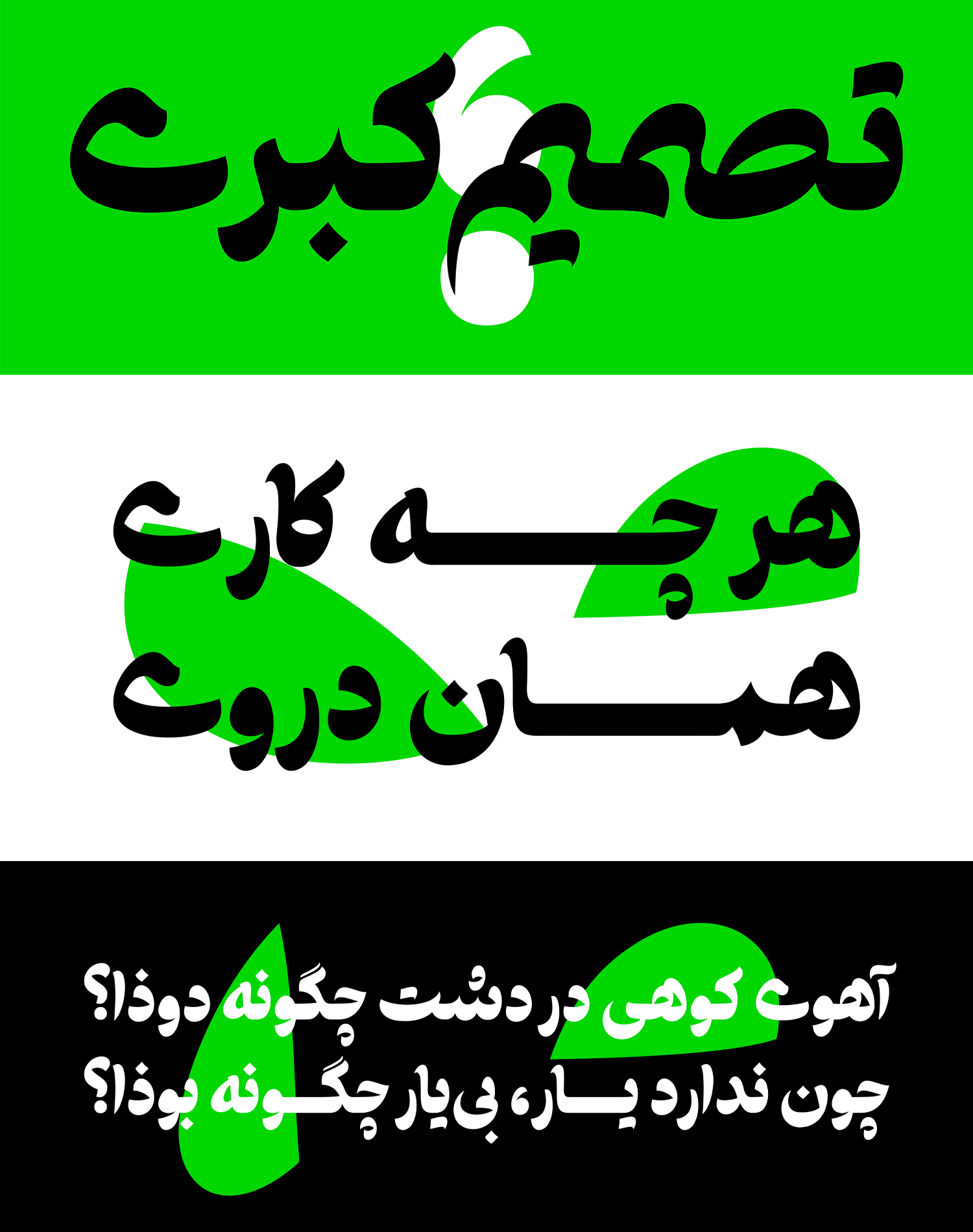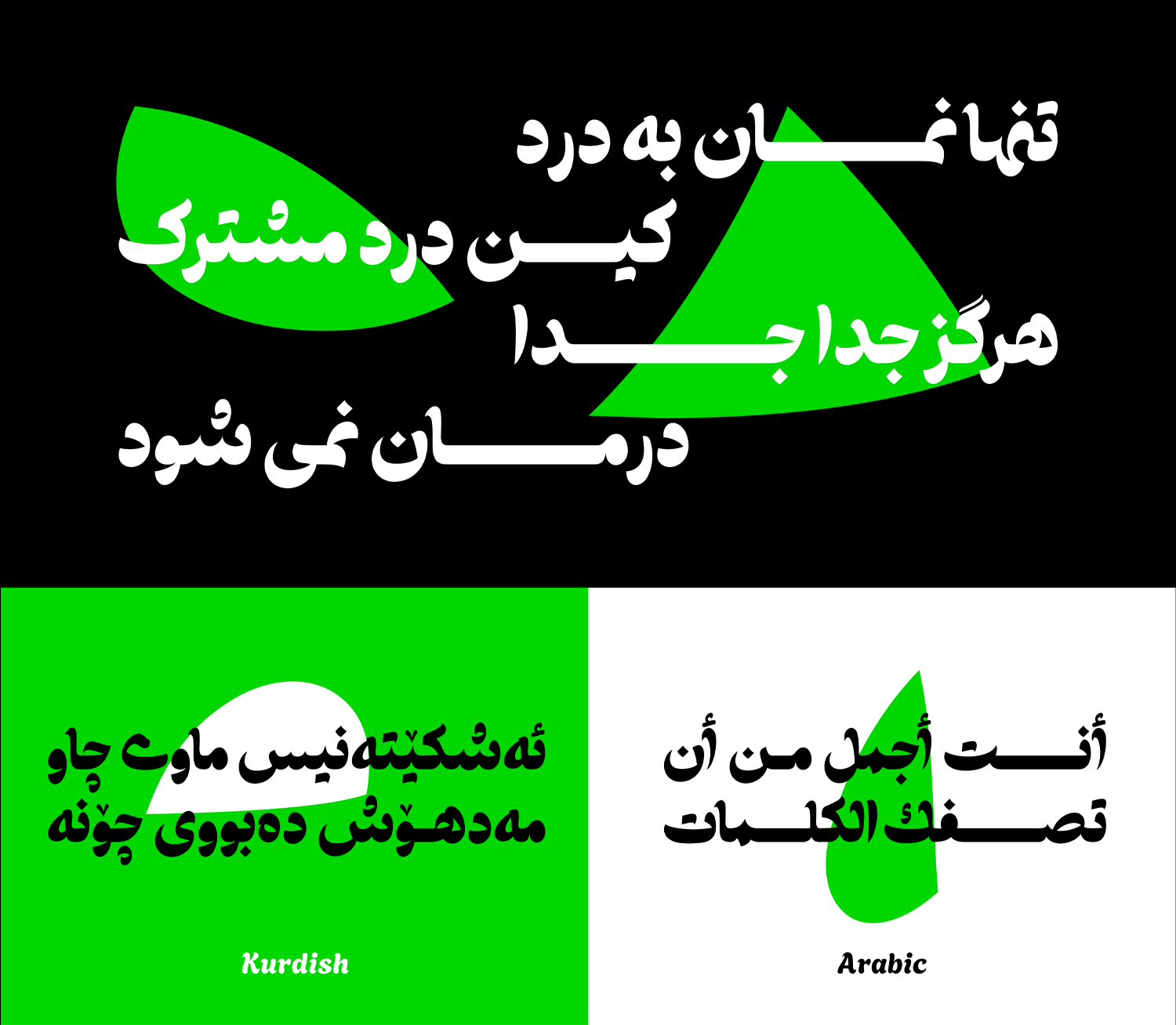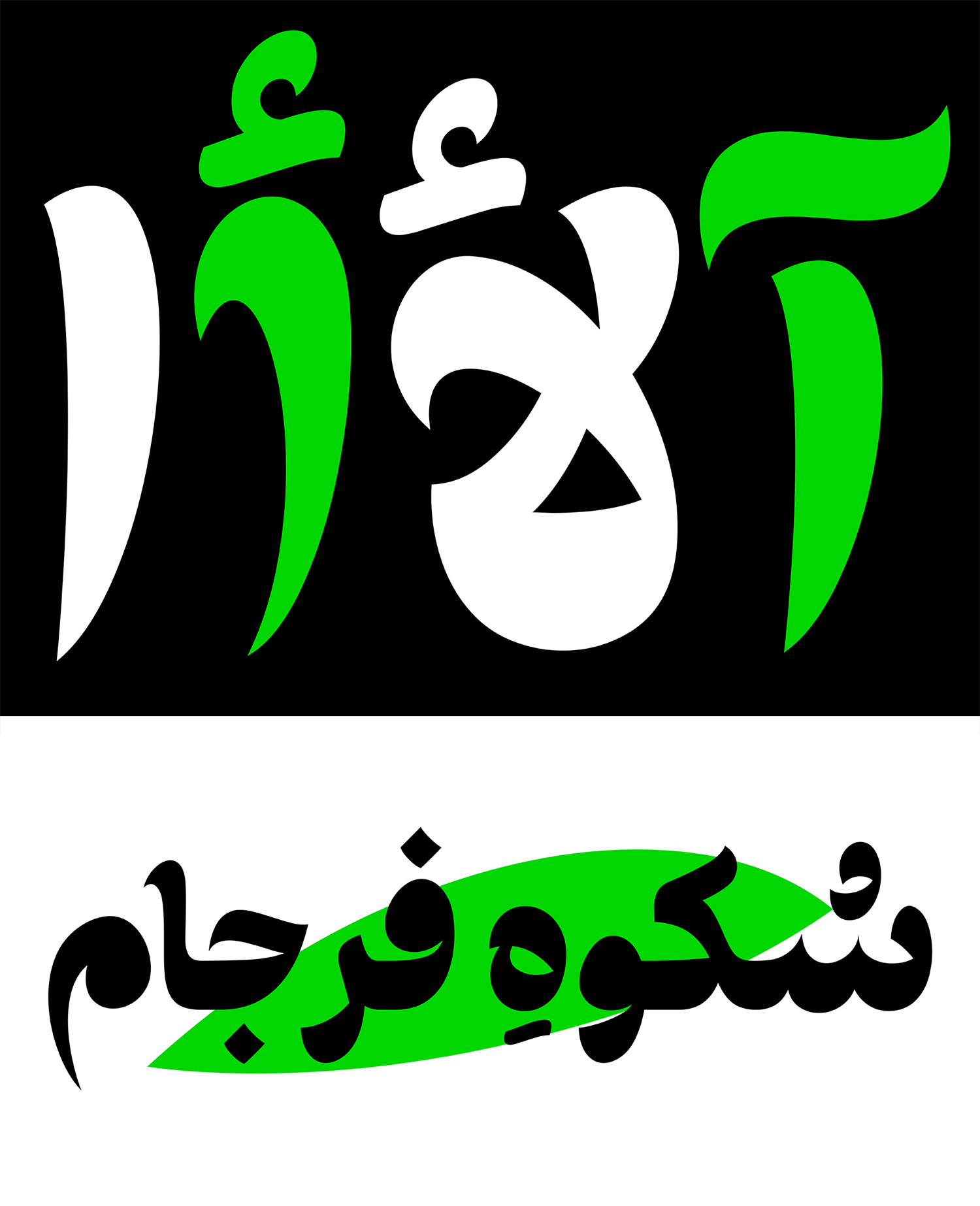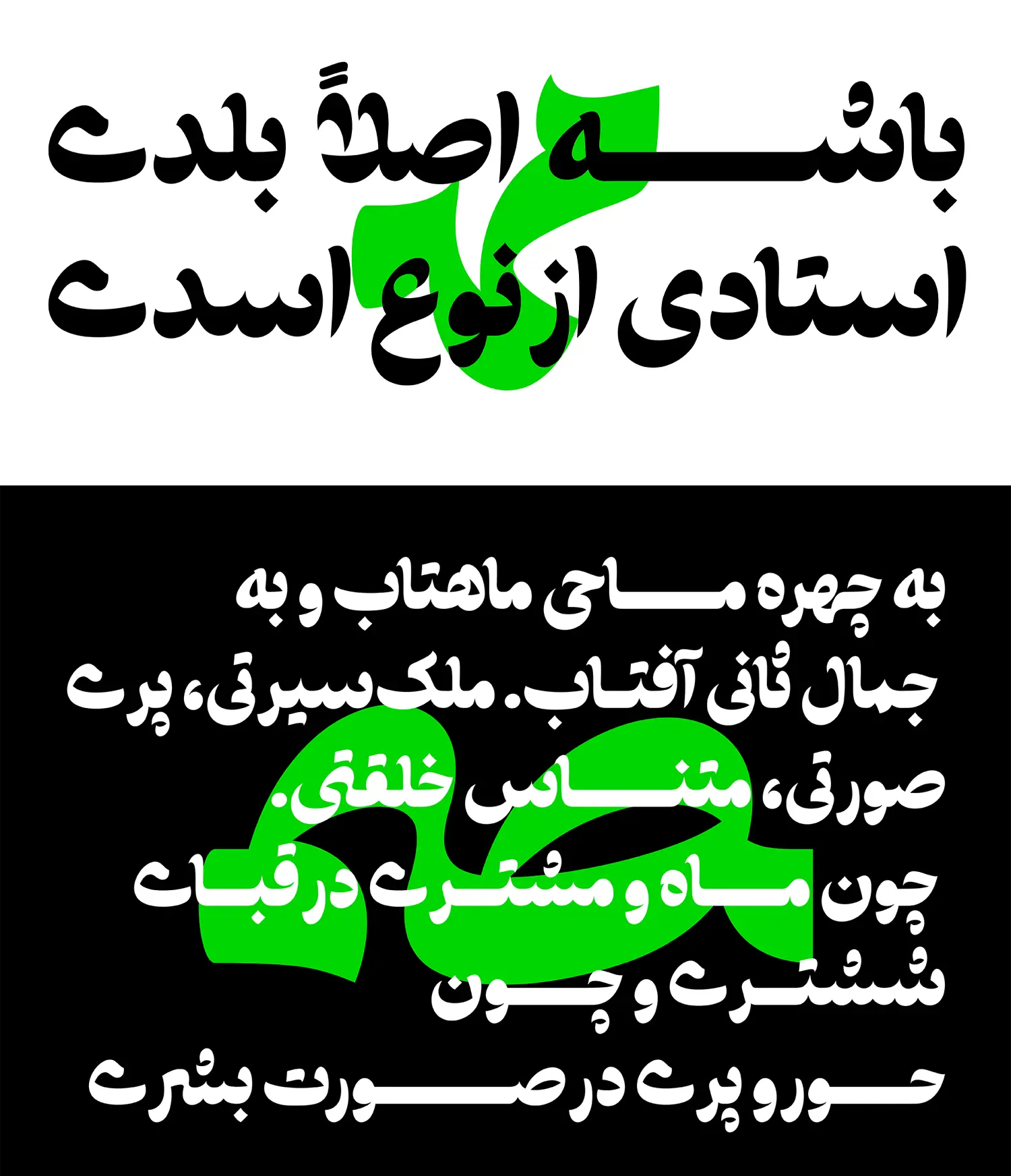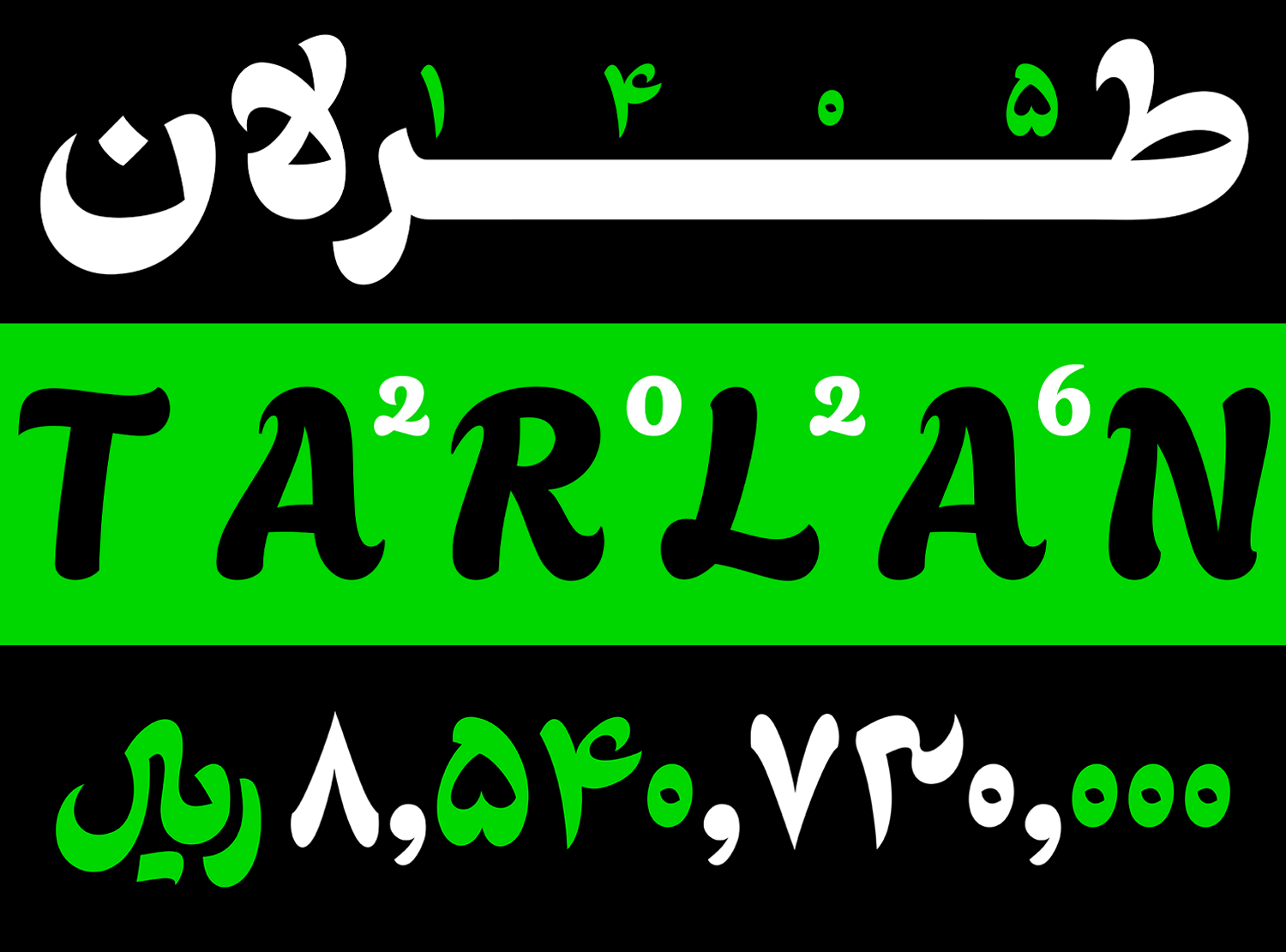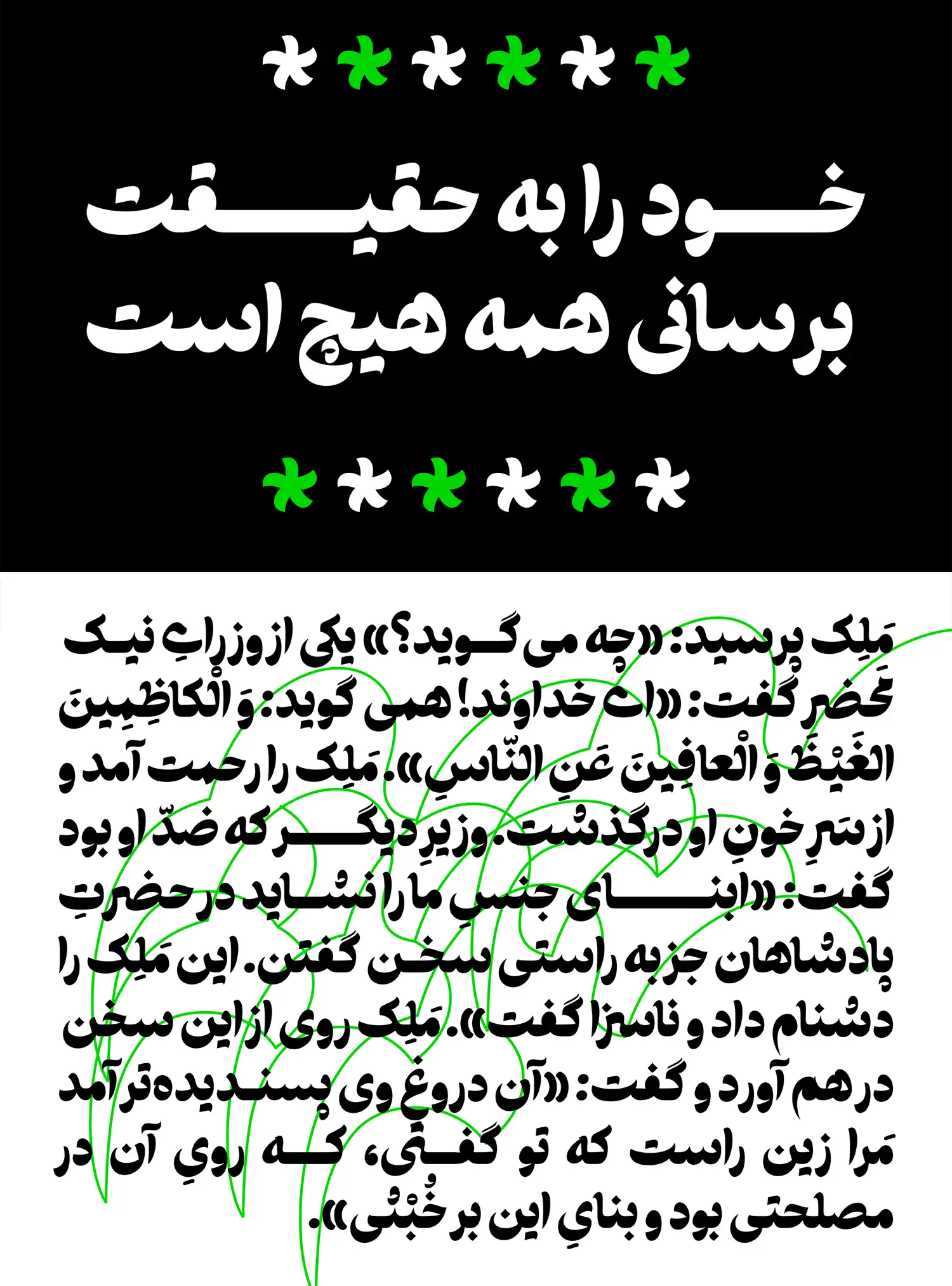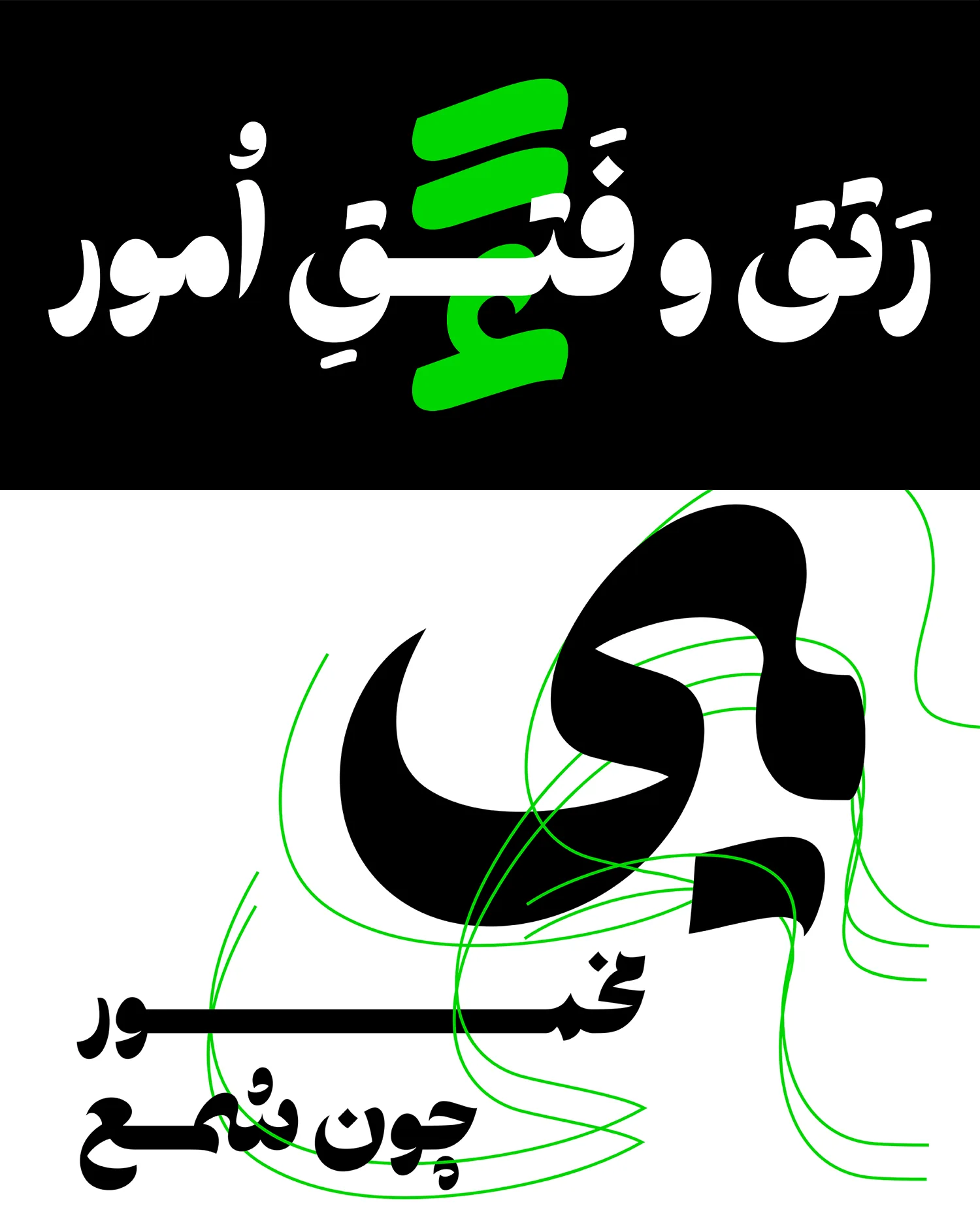
فونت طرلان (Tarlan)
فونت طرلان (به انگلیسی: Tarlan) از سری فونتهای جدید و مدرن امروزی است که بهجای تقلید از خطوط نسخ قدیمی یا مدرنسازی تکراری چنین خطوطی، هویت مختص خود را فریاد میزند. این فونت با باطنی دستنویس، گذشته خود را بهگونهای مدرن و نرم یادآور میشود.
از فونت طرلان میتوانید برای موضوعاتی که جنبه صمیمیت و ایجاد ارتباط با مخاطب دارند استفاده کنید. تبلیغات محیطی و فضای دیجیتال، خصوصا در عناوین یا طراحی پوسترها، این فونت را به اصری خارقالعاده تبدیل کرده است.
نقد و بررسی فونت طرلان (Tarlan)
فونت فارسی طرلان حاصل قلمزدنهای متعدد با مرکب و تجربه مستقیم بر روی کاغذ است. وحید یعقوبلو با ایدهپردازی و طراحی اولیه و امین عابدی با توسعه و فنیسازی آن، اثری خلق کردهاند که بیآنکه خود را مجذوب و محصور در قواعد یک خط سنتی خاص کند، عصاره و حافظه بصری خطوط سنتی مختلف را در قالبی پویا ارائه میدهد.
نام «طرلان» به معنای شاهین و پرندهای تیزبین، دقیقا پس از کامل شدن ساختار حروف انتخاب شد؛ نامی که اصالت، پویایی و انتهای تیز و پرانرژی قلم را به زیبایی روایت میکند.
بررسی هویت بصری و ویژگیهای ساختاری
اگر به تصاویر پیشنمایش این فونت دقت کنید، بررسی این نمونهها و فرم حروف طرلان، چند نقطه عطف مهم را آشکار میسازد:
- تناسبات فشرده و قوسهای پیوسته: حروف در طرلان ساختاری منسجم و فشرده دارند که باعث میشود کلمات کنار هم، ریتمی منظم و در عین حال روان ایجاد کنند.
- انتهای تیز قلم و حس دستنویس: برشهای انتهای حروف و حرکات قلم، حس زنده بودن خط دستی و سنت خوشنویسی با قلمنی و مرکب را منتقل میکنند.
- حضور قوی در عین حفظ خوانایی: طرلان یک تایپفیس تکوزن (Single Weight) است که تمرکز خود را روی جلب توجه در عناوین قرار داده، اما به لطف فرمشناسی دقیق، خوانایی متنهای کوتاه و نیمهبلند را نیز حفظ میکند.
امکانات و ویژگیهای فنی
توسعهدهندگان این فونت، نیازهای مختلف کاربران و طراحان را در نظر گرفته و بسته فونت را در دو نسخه مجزا ارائه دادهاند:
- نسخهی اصلی (TARLAN): این نسخه شامل جایگزینها (Alternatives) و ترکیبات هوشمند (Ligatures) به صورت پیشفرض است. اگر به دنبال تجربه کامل هنری، ترکیبات روان و فرمهای هوشمندی هستید که طراحان مد نظر داشتهاند، این نسخه بهترین گزینه برای پروژههای گرافیکی شماست.
- نسخهی پایه (Tarlan-Base): در این نسخه ترکیبات خودکار و جایگزینهای هوشمند غیرفعال شدهاند تا حروف در فرم استاندارد و سادهتر خود نمایش داده شوند. این نسخه برای کاربرانی که کنترلی یکدستتر بر روی متن میخواهند یا در محیطهای وب و نرمافزاری خاص فعالیت دارند، بسیار کاربردی است.
سایر ویژگیهای کلیدی:
- پشتیبانی چندزبانه: طرلان پوشش کاملی از زبانهای فارسی، عربی و کردی دارد. برای زبان انگلیسی نیز از یک فونت با ساختاری نزدیک استفاده شده است.
- اعداد اختصاصی: پشتیبانی کامل از اعداد فارسی و انگلیسی همراه با نسخه مخصوص اعداد فارسی هکشده که در واقع اعداد انگلیسی در این نسخه الزاما به فارسی تایپ میشوند. این نوع فایل فونت برای نرمافزارهای مالی یا استفاده در محیطهایی که الزاما نیاز به اعداد فارسی دارید مناسب است.
فونت طرلان برای چه کاربردهایی مناسب است؟
شخصیت بصری خاص و پویای طرلان باعث میشود که در فضاهای گرافیکی زیر عملکردی درخشان داشته باشد:
- طراحی عناوین و تیترها: جلد کتاب، نشریات، بستهبندی محصولات و پوسترهای نمایشگاهی.
- طراحی هویت بصری و لوگوتایپ: ایدهآل برای برندهایی که به دنبال لحنی اصیل، جسورانه و ماندگار هستند.
- تبلیغات و کمپینهای محیطی: بنرهای تبلیغاتی شبکه اجتماعی، بیلبوردها و شعارهای تبلیغاتی.
- متنهای کوتاه تا نیمهبلند: طراحی پستهای اینستاگرام، نقل قولها، متون ادبی و اشعار.
- فرم مستقل و غیرتکراری: برخلاف بسیاری از فونتهای بازآفرینی شده، طرلان کپی هیچ خطی نیست و هویت بصری کاملا منحصربهفردی دارد.
- انعطافپذیری در طراحی: وجود دو نسخه Base و Smart دستیابی به ترکیبهای متفاوت را در نرمافزارهایی مثل فتوشاپ و ایلاستریتور بسیار آسان میکند.
- پیادهسازی تمیز در زبانهای مختلف: پشتیبانی کامل از حروف کردی و عربی دست طراحان را برای پروژههای فرامرزی و منطقهای باز میگذارد.
جمعبندی
فونت طرلان ترکیبی هوشمندانه از یادگارهای سنتی و جسارتهای modern است. اگر برای پروژههای بعدی خود به دنبال قلمی هستید که در نگاه اول جلب توجه کند، لحنی گرم و دستنویس داشته باشد و در عین حال ساختاری کاملاً حرفهای ارائه دهد، فونت Tarlan یکی از بهترین گزینههای پیش روی شماست.